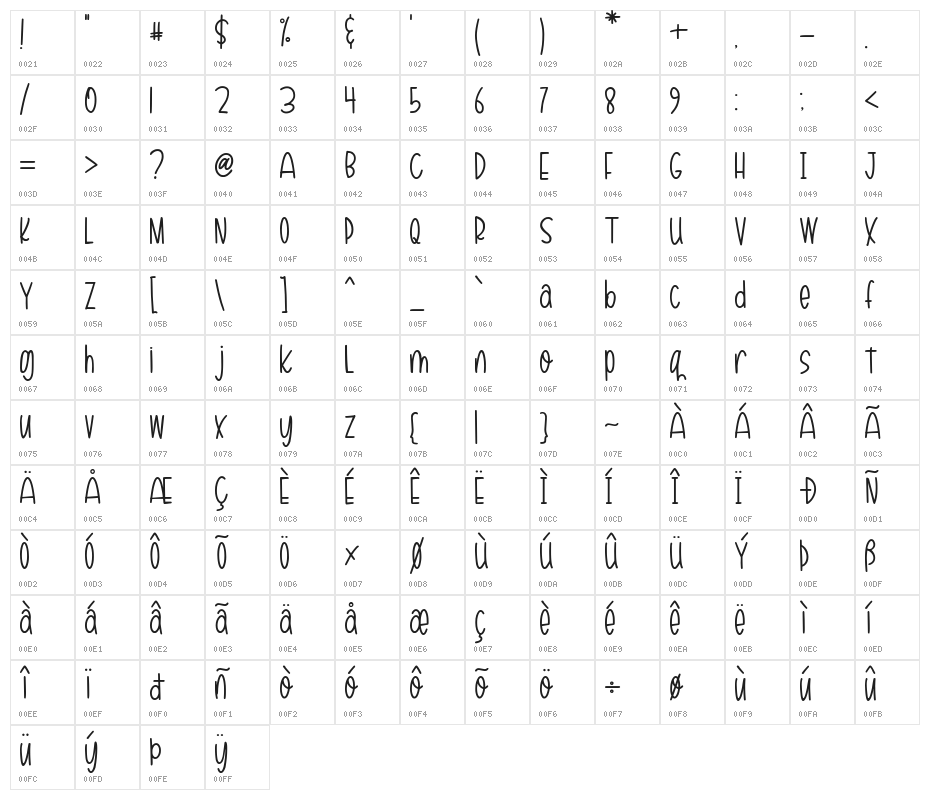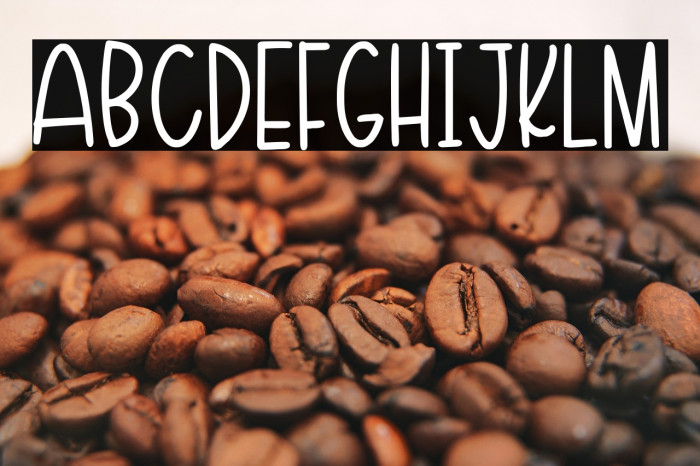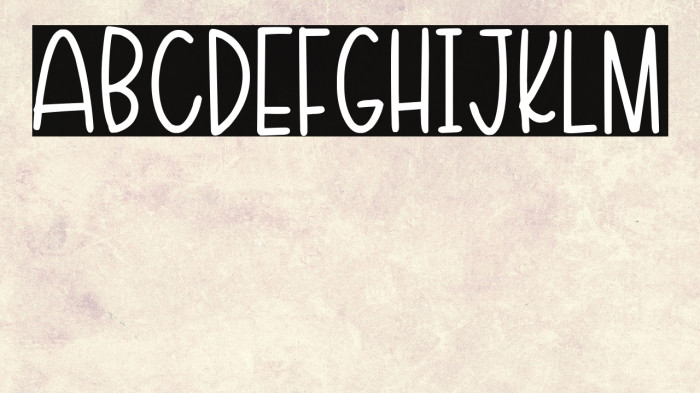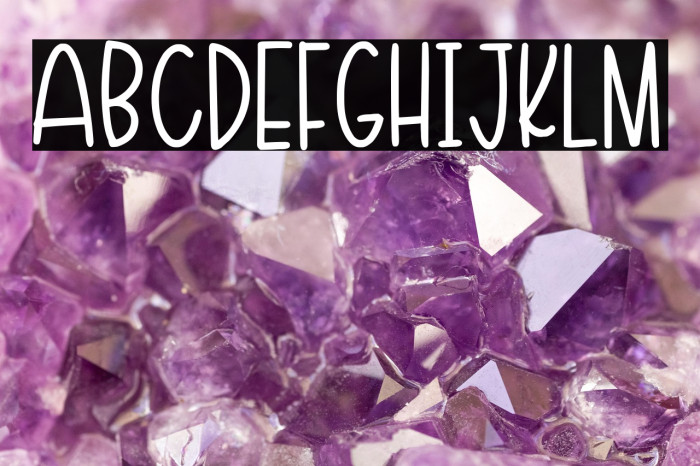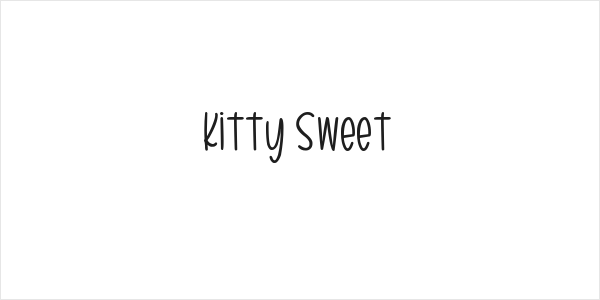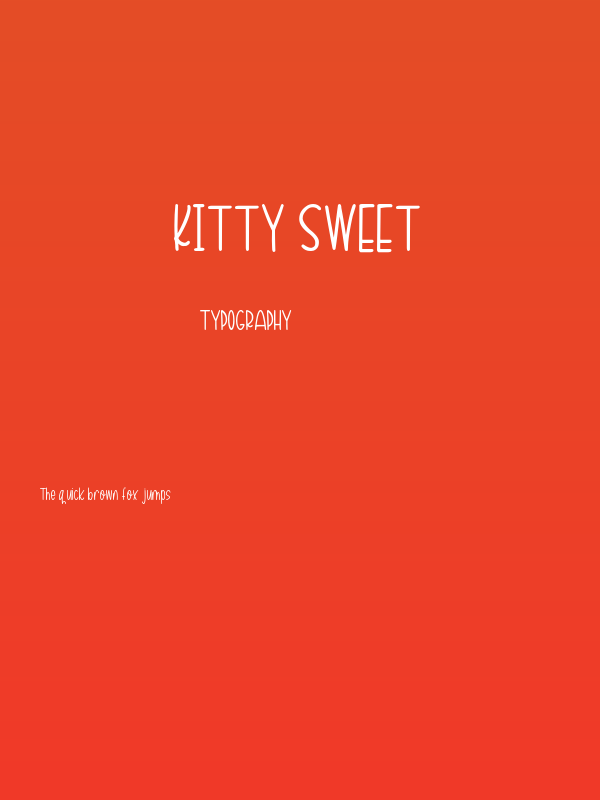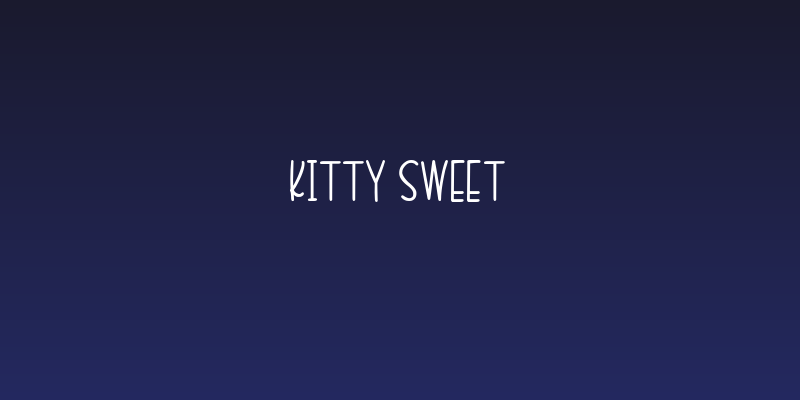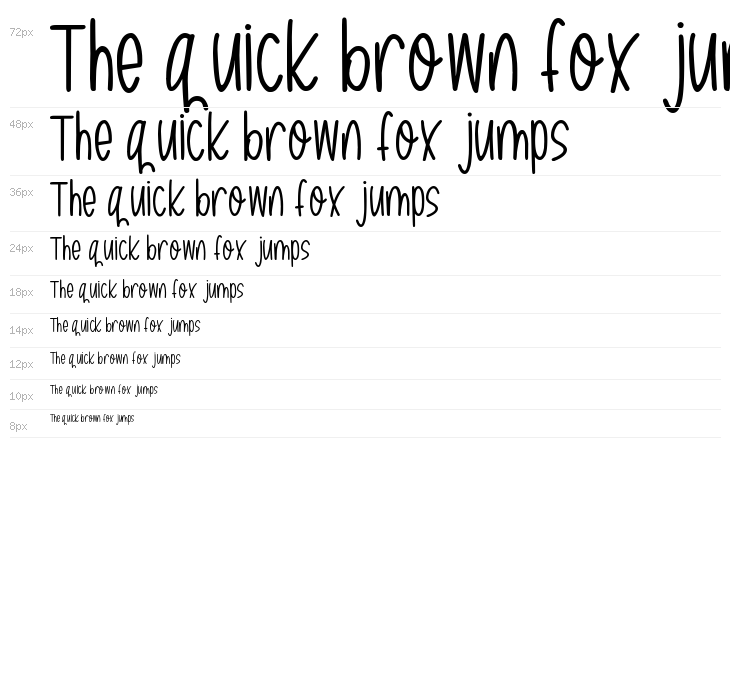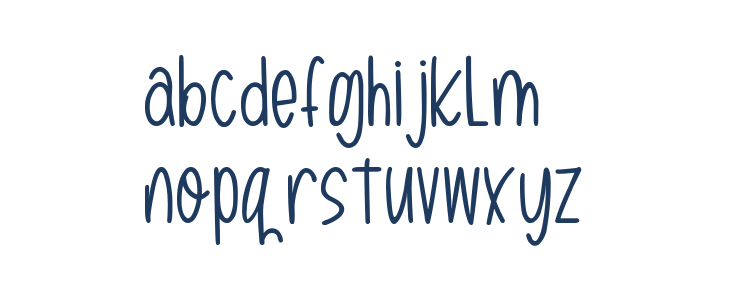
Kitty Sweet Font
| Stil general | Casual and playful |
| Caz de utilizare | Headlines, Logos, Informal text |
| Proiecte propuse | Ideal for greeting cards, children's books, playful branding, and social media graphics. |